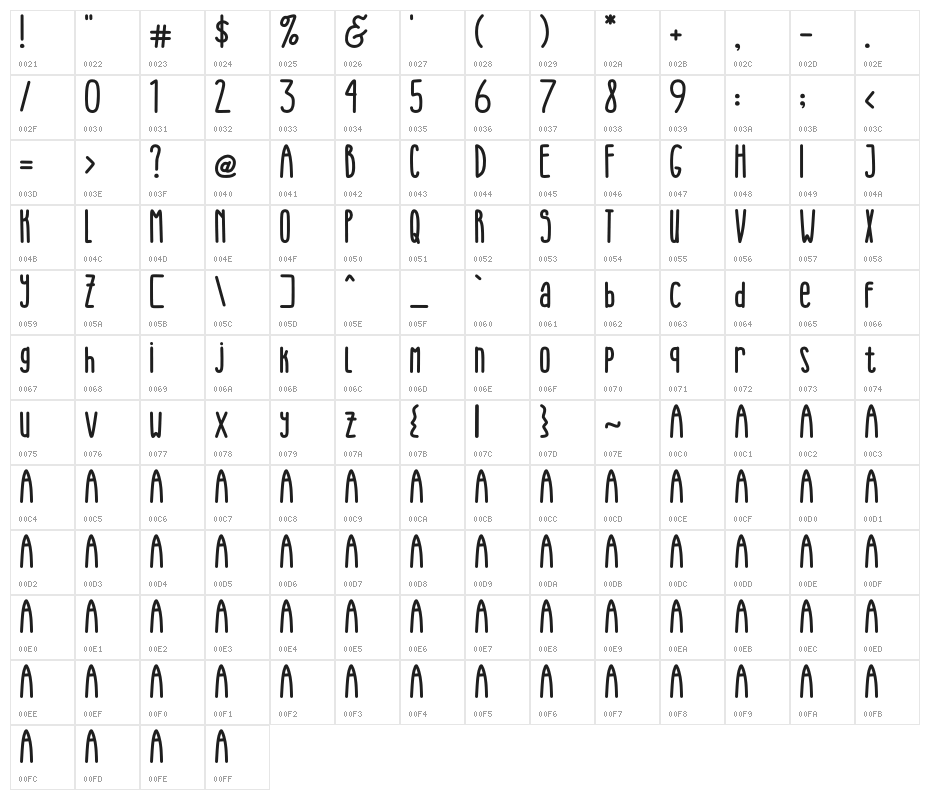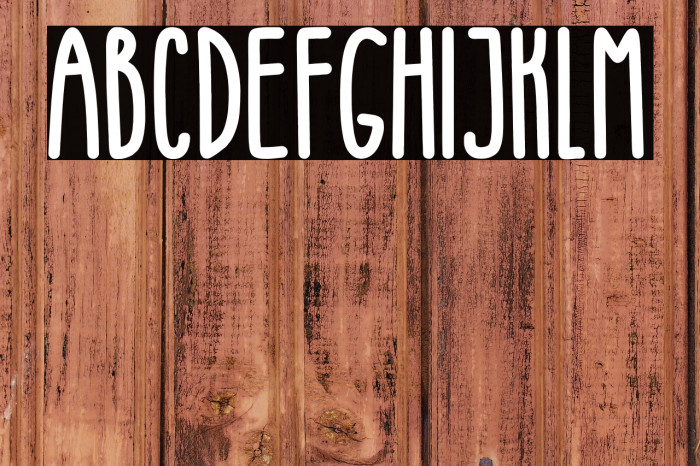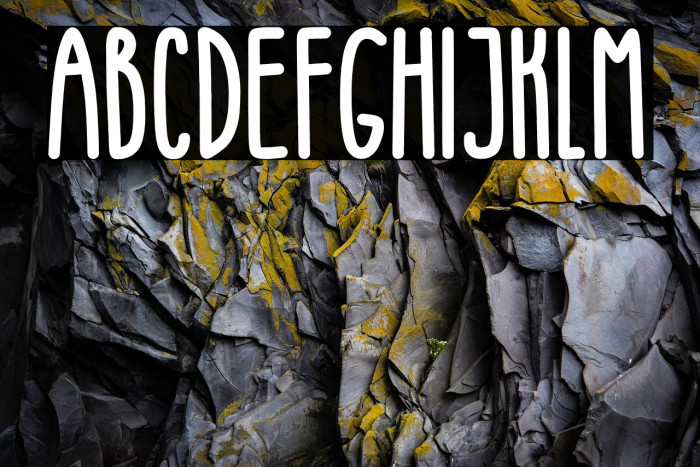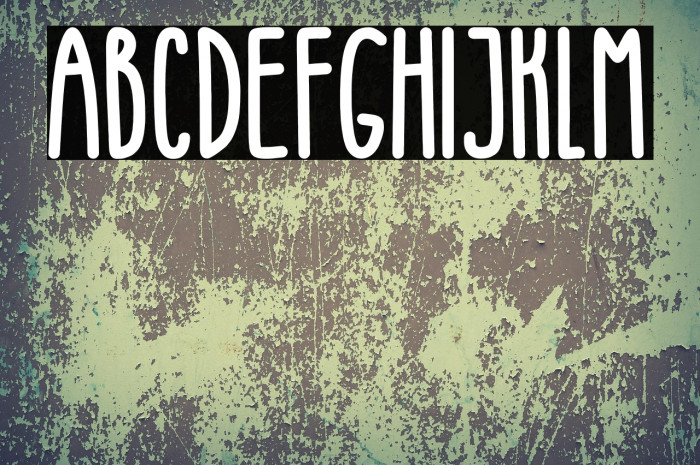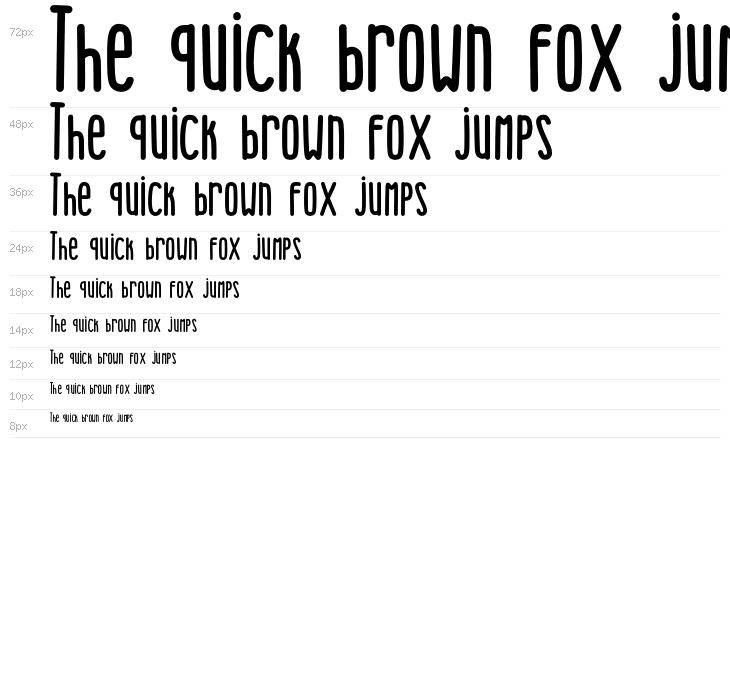
RedHead Snake Font
| Gesamtstil | Modern, Playful |
| Vorgeschlagene Projekte | Ideal for children's books, playful branding, creative posters, and social media graphics. |